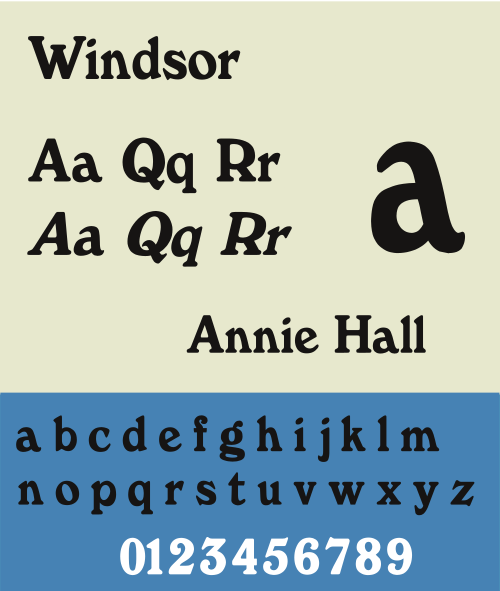
| カテゴリ | セリフ |
| 分類 | 画面 |
| デザイナー | エリシャ・ペチー |
| 鋳造所 | スティーブンソン・ブレイク |
| 作成日 | 1905 |
ウィンザーは、エリシャ・ペチー(1831-1902)によって作成され、スティーブンソン・ブレイク活字鋳造所によってリリースされたセリフ 書体です。[1]本文ではなく、表示や見出しなどの使用を目的としています。
大文字のMとWは広く広がっており、PとRは上部のボウルが非常に大きい。ウィンザーフォントの小文字のa、h、m、nは右手のステムが斜めになっており、 eは横線が斜めになっている。ビットストリームは、デジタル化のリリースノートでこれを「旧形式の創造的なバリエーション」と呼んでいる。[2]
リリース
Linotype、Elsner+Flake、URW++ 、Mecanormaなど、さまざまなフォントメーカーがバージョンをリリースしています。初期のデジタル化の多くは再ライセンスされていたため、これらのうちいくつかは、異なる権利保有者によって販売された同じデジタル化であり、文脈合字の置換などの最新機能でアップグレードされている可能性があります。コンデンス、アウトライン、ボールドなど、さまざまなウェイトが作成されています。[3]
ウィンザーとも呼ばれる無関係の書体は、1960 年にインタータイプ社のためにエドウィン W. シャールによってデザインされました。
マイルズ・ニューリンはウィンザー書体をベースにニュースピリット書体をデザインした。[4]
大衆文化では
- 1977年の『アニー・ホール』以降、ウディ・アレンの映画のタイトルやクレジットのほとんどには、黒の背景にまばらな白いウィンザーライトコンデンスフォントが使われている。[5] 2007年の著書『Mere Anarchy』のEbury Press 2007年版(ISBN 0091920213 )でも同じフォントが使われている。[6]
- Windsor Bold は、テレビシリーズ「All in the Family」、「227」、「The Goldbergs」のタイトルとクレジットに使用されています。[要出典]
- Windsor Bold は、テレビシリーズ「Who's the Boss?」のエンディング クレジットに使用されています(オープニング クレジットでは Monotype Goudy Catalogue が使用されています)。[要出典]
- 1968年から1972年にかけて発行された『Whole Earth Catalog』の表紙にはウィンザーフォントが使用されていた。[要出典]
- ニューヨーク市のマックス・カンザス・シティは、1965年から1981年まで、ロゴに小文字のウィンザー・ボールドを使用していました。[引用が必要]ミネソタ州ミネアポリスのファースト・アベニュー・ナイトクラブの7th Street Entryも、1981年からロゴに小文字のウィンザー・ボールドを使用しています。[引用が必要]
- 『モンティ・パイソン・アンド・ホーリー・グレイル』の「インターミッション」カードでは、Windsor Bold フォントが使用されています。
- ウィンザーボールドは、1980年代のトレーディングカードシリーズ「ガーベッジ・ペイル・キッズ」でも使用された書体である。[7]
- 『ザ・プライス・イズ・ライト』は、放送期間の大半、および1975年に1時間に拡大されて以降、オープニングでウィンザーのフレーズを流した。当初、「One Hour」というフレーズは未知のスクリプトフォントで流されたが、1975年12月中旬までにウィンザーの「Hour Power」に変更され、2009年にオープニングタイトルが廃止されるまでこのフォントが使用され続けた。一部のエピソード、特にスペシャルでは、1990年代後半から代わりにクーパーブラックが使用されたが、これは2007年秋に廃止された。
- ウィンザーの凝縮版は、パーカー・ブラザーズの1978年のゲーム「パンチライン」の文字ストリップに使用されている。[8]
- セサミストリートでは、ウィンザーフォントがオスカー・ザ・グラウチのアルバム「Let a Frown Be Your Umbrella」のカバーに使用されました。
- ウィンザーのより重いバリエーションは、ヘルボーイシリーズのミニ見出しや代替ワードマークとして時々使用されます。[9] [10]
- このフォントは、Ed Emberleyの「Go Away, Big Green Monster!」のストーリーテキストで使用されています。
- このフォントには、 The Criticのクレジットで使用されている細長いバージョンがあります。